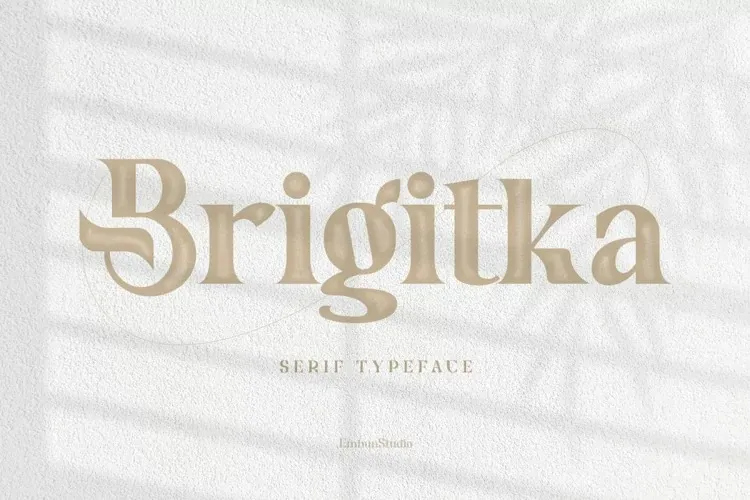
A Brigitka é uma tipografia serif que oferece um toque do passado cultural, resultando em um estilo clássico e moderno. Desenvolvida pelo 99designs, a fonte Brigitka se destaca por sua elegância minimalista e sofisticada, tornando-a perfeita para design gráfico de alta qualidade. Ideal tanto para criações simples e limpas como para designs detalhados e elaborados, essa font é ideal para uso em logotipos, materiais de marca, cartões de visitas, cartões de convite, camisetas, capas, miniaturas, impressão, panfletos, fotografias, citações e muito mais. A Brigitka é uma escolha ótima para designers que valorizam um estilo moderno e sofisticado. Ela traz uma vibe única que vai se destacar em qualquer projeto visual. Descubra por si mesmo como a Brigitka pode revolucionar seu próximo design!